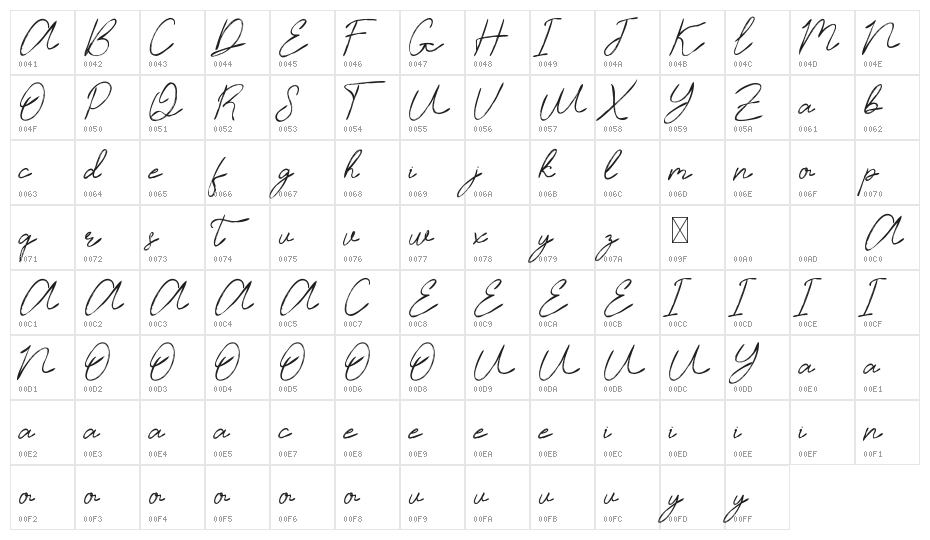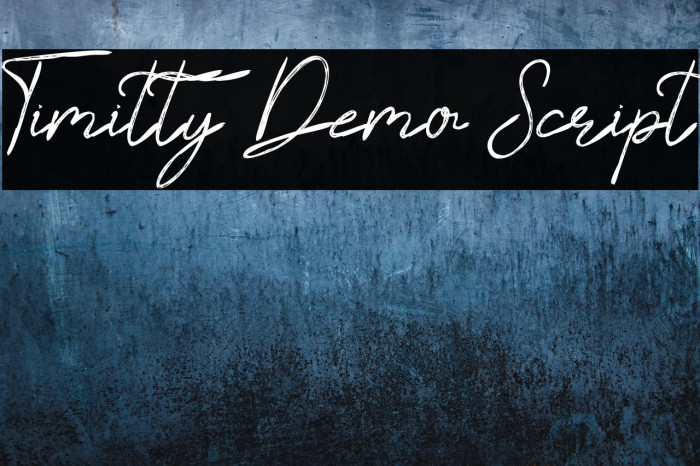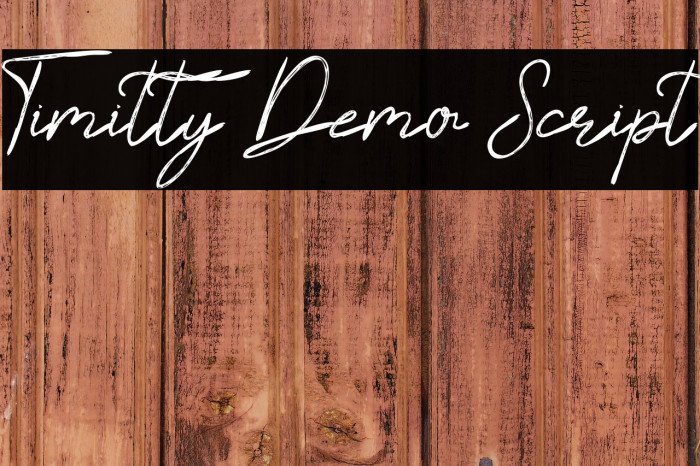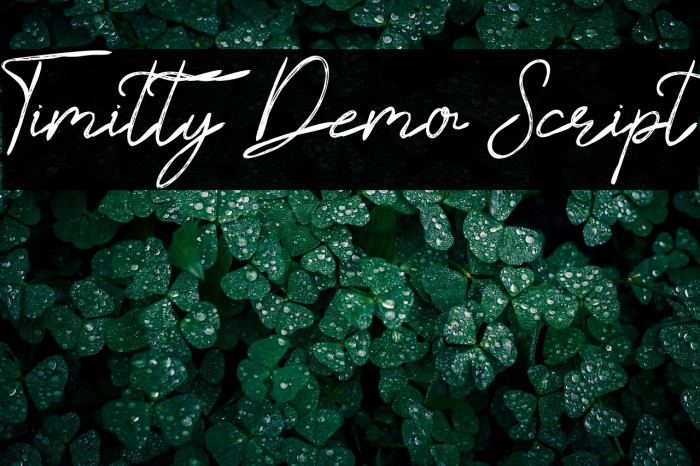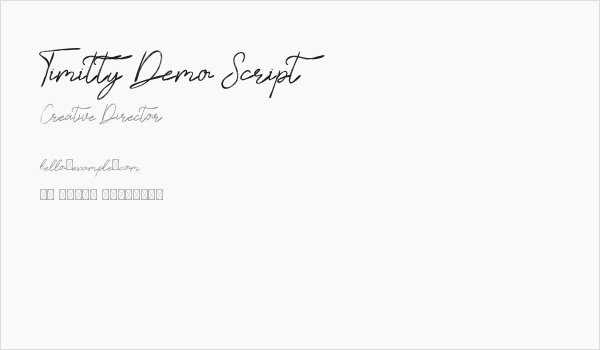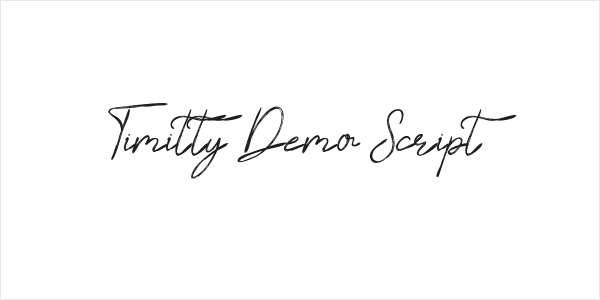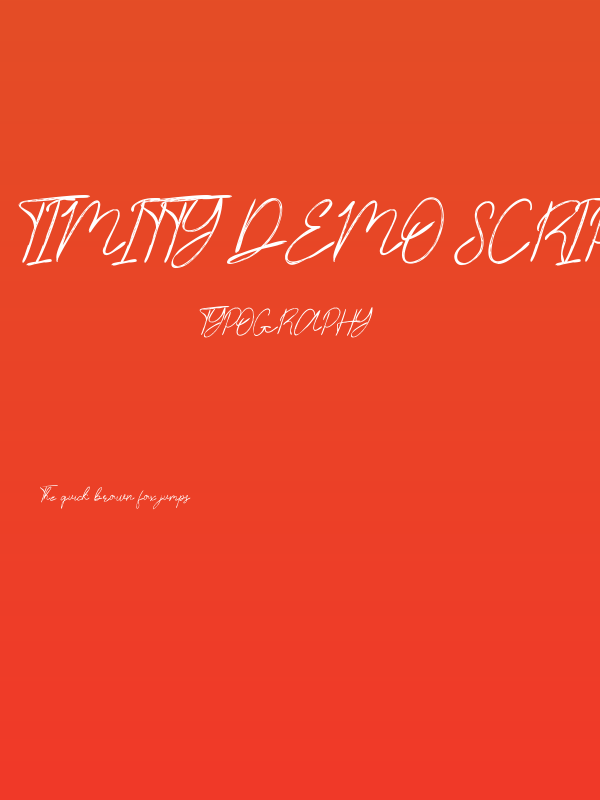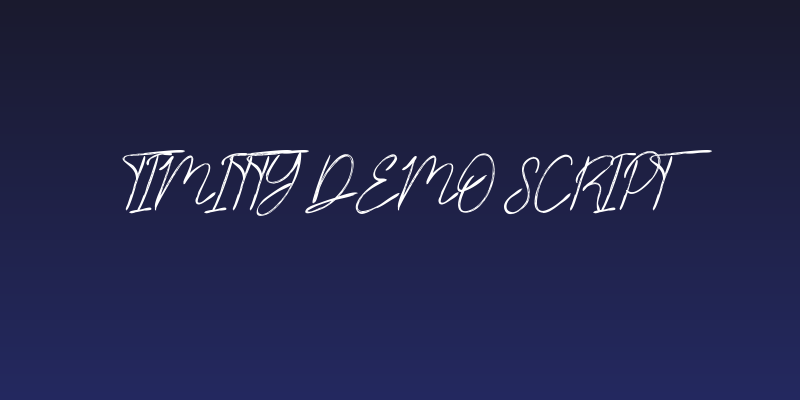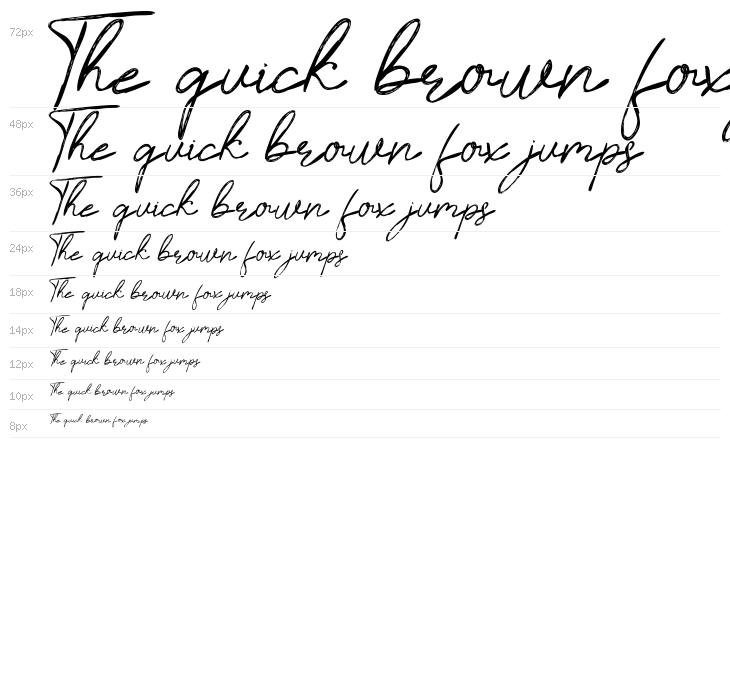
Timitty Demo Script Font
| Stile generale | Elegant, Handwritten |
| Caso d'uso | Logos, Invitations, Personal Branding |
| Progetti proposti | Ideal for wedding invitations, personal branding, greeting cards, and elegant stationery. |